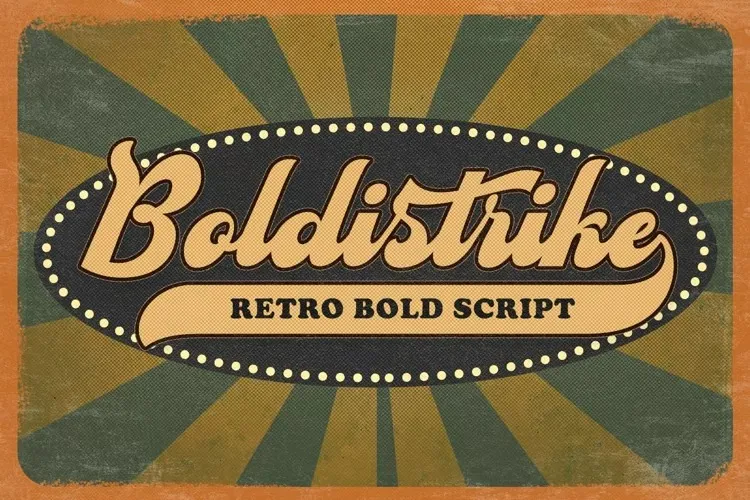
Boldstrike Font – Download Grátis
Esta é uma fonte script bold cuidadosamente criada com um toque elegante. Foi desenhada e compartilhada pela Letterhend. Com letras marcantes e traços curvados, essa tipografia destaca-se para projetos de temática retro. A Fonte foi perfeitamente concebida para ser aplicada em logotipos, bem como outros formatos formais como convites, rótulos, selos, revistas, livros, cartões de aniversário e casamentos, embalagens, moda, maquiagem, estoquinhos, romances ou qualquer tipo de propósito publicitário. Seja você criador de design gráfico, editor de revistas, designer de materiais em linha, este fonte certamente será uma ferramenta valiosa para incorporar um toque único e diferenciado a seus projetos.